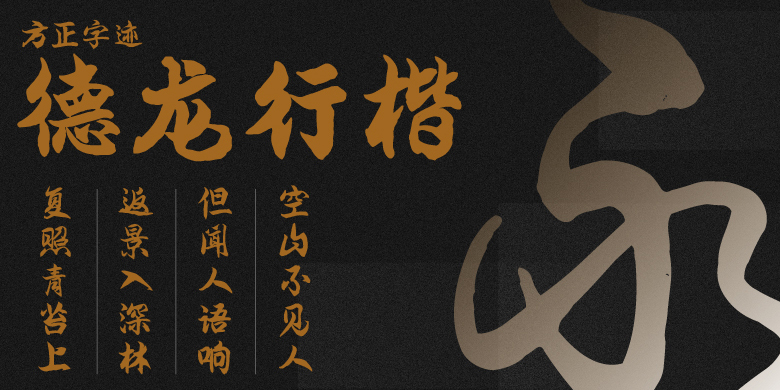
方正字迹-德龙行楷
字体品牌: 方正字迹 设计师:孙德信,孙海永 字体分类:行楷、行书 字体属性:精品字 字符集:大陆简体(GB2312-80)、简繁扩展(GBK) 发布时间: 2022
方正字迹德龙行楷,是在汉字楷书的基础上添加了行书的笔意,点画线条多变,广泛易懂,富有创意。字体强化了字体的精神面貌,增强了字的书法使用性;加大了汉字笔法的美观大方,活泼刚劲的力度;加深了审美的解读灵活多变,耐人寻味。沿用了唐晋风范,笔笔有出处,字字有根源。怎耐是群星灿烂,光辉照人。弘扬传承,民之愿,国之兴。
而更适合于电影海报、包装设计、品牌名称、微信端等各类商业海报,户外广告体及刋头大字广泛应用。